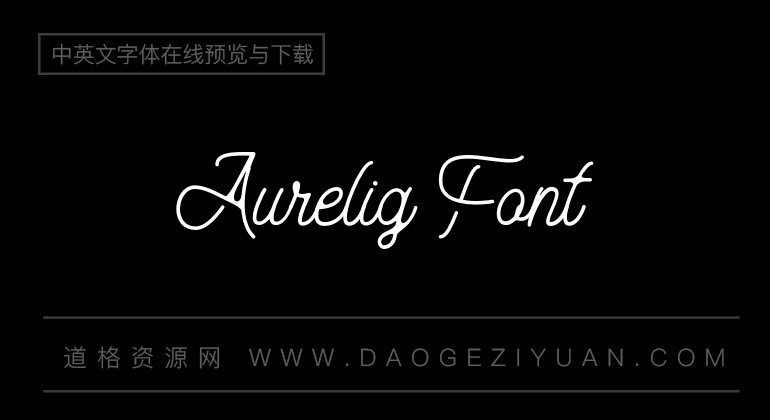
Aurelig Font
Aurelig Font 是一种优美的手写风格字体,具有时尚和现代感。它的设计师是 Luciano Vergara,他是一名来自智利的资深字体设计师。 这种字体的特点是流畅连贯的线条和笔画,字母之间的间距适中,使得阅读起来非常容易。它的字母形状非常有特点,有点像手写的草书,但同时也很规整。这种字体适合用于标题、广告、印刷品和品牌标识等许多场合。 Aurelig Font 提供了多种字重和风格,包括正常、粗体、斜体和粗斜体等,以满足不同的设计需求。
Aurelig Font是一款非常不错的手写艺术字体,具有很好的视觉感,适合于文化类的宣传设计、商业类品牌的广告和产品包装设计以及个性化文字排版等较多场景。